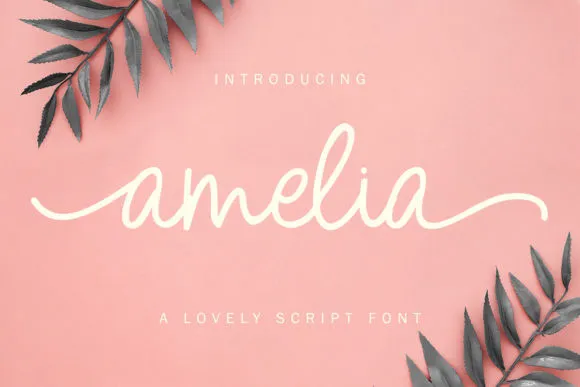
Amelia – Lovely Script Font – Fonte Grátis
Amelia - Lovely Script Font
Estamos muito felizes por oferecer a você a Amelia – uma fonte do tipo script delicada e charmosa criada com mão. Esta fonte é ideal para aqueles que buscam um toque personalizado em seus projetos, proporcionando um aspecto autêntico ao seu design. Com um design elegante e farto de detalhes, Amelia é perfeitamente adequado para uma variedade de aplicações. Seja para assinaturas, cartões de papelaria, logotipos ou até mesmo para capas de livros, revistas e sites, a Amelia irá dar um toque único ao seu trabalho. Estamos ansiosos para ver sua obra com esta fonte, que é uma perfeita escolha para qualquer projeto em que você está trabalhando. Teste-a agora para entender como ela pode tornar o próximo projeto de design mais especial e autêntico. Seja qual for a área do seu trabalho, a Amelia – Lovely Script Font é certamente algo que você não vai querer deixar de lado.